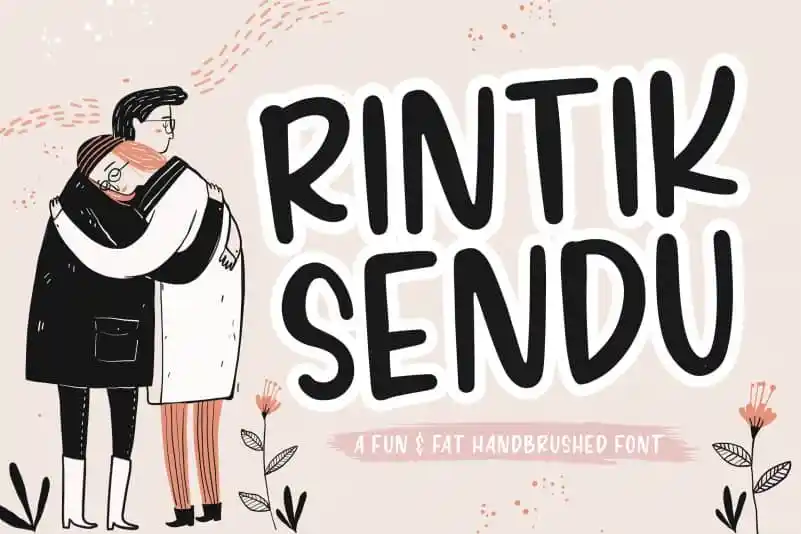
Rintik Sendu Handbrushed Font – Download Grátis
A fonte Rintik Sendu Handbrushed Font é uma deliciosa escolha para designers que buscam adicionar um toque único às suas criações digitais. Seja você criando embalagens de produto sofisticadas ou projetos de marca inovadores, o Handoobushed da Rintik Sendu oferece um tom natural e autêntico perfeito para qualquer ambiente visual. Essa fonte elegante ganha vida através das influências modernas e da arte livre. Suas linhas suaves permitem que você faça uma transição fluida entre o texto impresso na frente e a imagem do fundo, criando um efeito visual incrível sem ser arranjado artificialmente. É perfeitamente adaptável para aplicar em qualquer projeto de publicidade, seja para anúncios no magazine ou posts nas redes sociais. A Rintik Sendu Handbrushed também é uma ótima escolha para se expressar na frente da cerimônia de casamento, onde a mão-de-ferro artística da fonte pode adicionar um toque personalizado e único. Se você está buscando uma maneira simples e elegante de destacar textos em projetos pessoais ou profissionais, Rintik Sendu Handbrushed é a escolha perfeita. Suas linhas fluídas e seus detalhes sutis trazem um ar autêntico ao seu trabalho, tornando-a uma fonte versátil que se adapta à diversos cenários de uso. Além disso, sua adequação para produtos de marca, publicações em jornais, mídias sociais e até mesmo eventos como casamentos, torna a Rintik Sendu Handbrushed um investimento valioso em seu arsenal gráfico.